Font typewriter là gì và những đặc trưng nghệ thuật khác biệt?
Font typewriter là hệ thống phông chữ mô phỏng lại nét chữ được tạo ra từ các máy đánh máy cơ học nổi tiếng của thế kỷ trước như Remington hay Underwood. Điểm đặc trưng lớn của dòng phông này là kiểu dáng Monospaced, nghĩa là mọi ký tự từ chữ “i” mảnh đến chữ “m” rộng đều chiếm một khoảng không gian ngang bằng nhau trên bản in.
Trong ngành đồ họa đương đại, bộ font chữ đánh máy ngày xưa không chỉ đơn thuần là công cụ soạn thảo mà còn là một ngôn ngữ nghệ thuật đầy tính tự sự. Các đường nét thường không nhẵn nhụi mà có độ nhám định, đôi khi đi kèm các vết mực loang nhẹ hoặc các nét đứt quãng li ti do tác động của phím gõ lên ruy băng mực. Chính sự “không hoàn hảo” này lại mang đến vẻ đẹp mộc mạc, chân thành và đầy tính xác thực cho thiết kế.
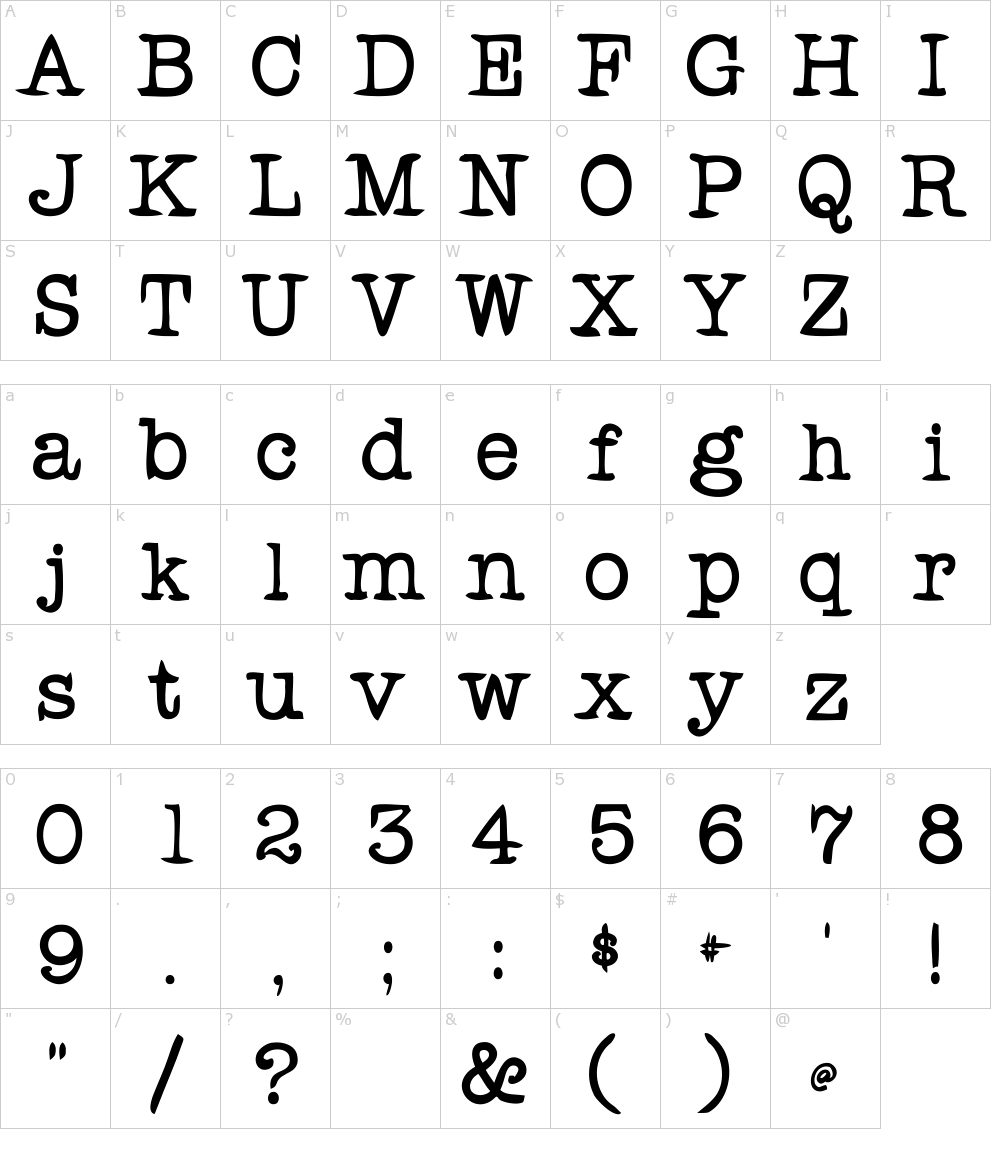
Lưu ý chuyên môn: Khi sử dụng bộ font typewriter Việt hóa cho in ấn bao bì hộp giấy, kỹ thuật viên nên kiểm tra mật độ các vết mực xước nhỏ. Việc duy trì sự rõ nét giữa các khoảng hở giúp thành phẩm không bị hiện tượng bết mực làm mờ nội dung thông tin.
04 Công dụng của phông chữ đánh máy trong thiết kế nhận diện thương hiệu
Sức hút của sự cũ kỹ mang lại chiều sâu và giá trị riêng biệt cho các ấn phẩm của doanh nghiệp, giúp nâng cao hiệu quả truyền thông trên nhiều phương diện:
- Sản xuất bao bì thực phẩm và cafe: Font chữ này là lựa chọn phù hợp cho các dòng túi giấy đựng cafe rang xay hoặc hộp đựng trà đặc sản. Hình ảnh chữ đánh máy in trên nền giấy Kraft tạo cảm giác về sản phẩm thủ công, sạch và giàu tâm huyết của người sản xuất, khơi gợi niềm tin về chất lượng tự nhiên.
- Thiết kế và in ấn thiệp tri ân, Voucher: Sử dụng phông chữ đánh máy cho các dòng thư ngỏ hay phiếu quà tặng mang lại sự chân thành đặc biệt. Khách hàng khi nhận được bản in này sẽ cảm nhận được sự trân trọng và phong cách riêng biệt của nhãn hàng thay vì các mẫu in công nghiệp thông thường.
- Khắc laser cá nhân hóa trên vật liệu gỗ và da: Các nét chữ font chữ đánh máy ngày xưa khi được khắc trên bề mặt gỗ hay bìa sổ da tạo nên độ sâu tinh xảo. Đây là giải pháp hiệu quả cho các dòng quà tặng doanh nghiệp mang phong cách hoài cổ và thanh lịch cho các hội nghị lớn.
- Xây dựng bộ nhận diện văn phòng phẩm: Từ danh thiếp, bìa hồ sơ đến tem nhãn niêm phong, phông chữ này giúp thương hiệu tạo dựng hình ảnh khác biệt, gợi nhắc về giá trị lịch sử lâu đời và sự bền bỉ của đơn vị trong mắt khách hàng đối tác.
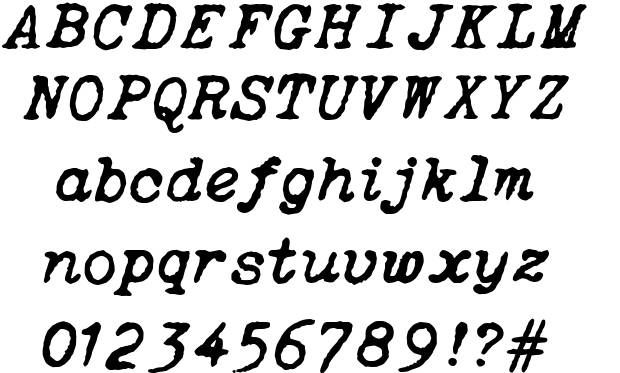
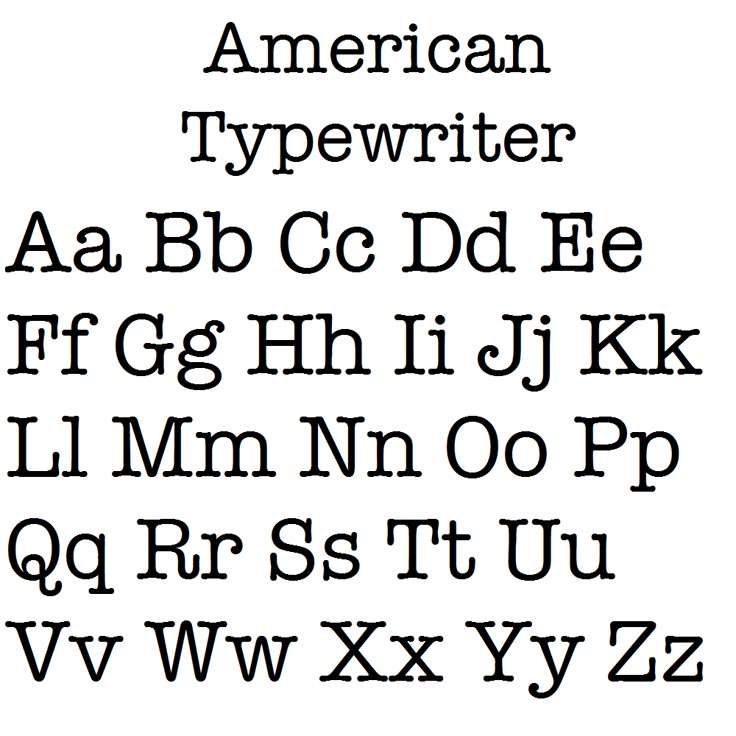
04 Lưu ý kỹ thuật khi in ấn font typewriter Việt hóa lên bề mặt vật liệu
Để thành phẩm sau in đạt độ mịn màng và trung thực với bản thiết kế, đội ngũ sản xuất cần chú trọng tránh những thiếu sót thường gặp sau đây:
- Kiểm soát độ dày nét xước: Font chữ đánh máy thường có các phần mực bị “nham nhở” một cách nghệ thuật. Nếu không kiểm tra độ dày đường path trong file vector, khi thực hiện in lụa hoặc in kỹ thuật số, các chi tiết này dễ bị bết mực vào nhau, làm mất đi tính đặc trưng của phông chữ trên thành phẩm sản xuất.
- Tối ưu đường Path cho gia công bế nổi: Một sai lầm phổ biến là không xử lý mượt các điểm neo trong file vector khi yêu cầu dập nổi logo trên nắp hộp giấy cao cấp. Việc để dư thừa điểm neo khiến khuôn bế không sắc nét, dễ gây hiện tượng nhăn mép giấy Ivory hoặc rách sớ giấy mỹ thuật của bao bì, làm hỏng bố cục trang trọng.
- Lệch hệ màu CMYK trên nền giấy thô: Chữ đánh máy thường dùng màu đen đặc hoặc xám chì. Trên các loại giấy có độ thấm mực cao, màu sắc dễ bị ngả sang tông xám mờ nhạt. Kỹ thuật viên tại xưởng cần thực hiện hiệu chỉnh tăng độ bão hòa màu đen (Rich Black) để nội dung luôn sắc sảo dưới ánh sáng phòng trưng bày.
- Thiếu vùng bù hao vùng cắt cho bao bì: Đặt các dòng thông tin quá sát mép thiết kế khiến thành phẩm dễ bị máy cắt phạm vào trong quá trình hoàn thiện túi giấy hoặc kẹp file tài liệu. Người thiết kế cần chủ động chừa vùng an toàn tối thiểu 5mm từ nội dung chính đến đường biên cắt để bảo toàn tính cân đối cho tổng thể thành phẩm in ấn.